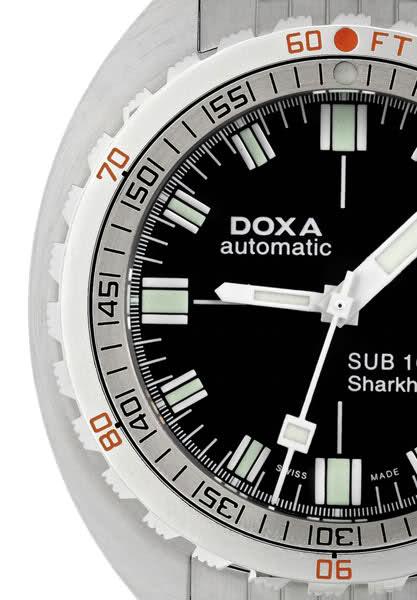
Suche dringend! Spezielle Typo aus den Spätsechzigern
Hallo zusammen, mein erster Beitrag in diesem Forum und gleich eine ganz kniffelige Frage:
Ich suche eine Schrift, die bei Doxa-Taucheruhren aussen auf der Drehlünette graviert ist. Doxa Taucheruhren gibt es seit 1967.
Ich habe schon öfters mal nach dieser Typo gesucht, konnte aber bisher leider überhaupt nichts finden. Sehr einprägsam ist bei dieser Schrift die Ziffer 4, die ich noch nie in der Form gesehen habe als ttf, otf, whatever.
Bei der gesuchten Schrift handelt es sich schoneinmal nicht um die Eurostile, Berthold Gothic oder andere bekanntere Fonts.
Hier ein Bild von der Doxa (ein ganz dolles Teil!) :biglove:
ich würde mal sagen das du diesen font zu 99% nicht finden wirst. das sind ja irgendwelche anfertigungen die direkt für das produkt entwurfen wurden, den ziffern lag sicher kein font zugrunde*. ähnliche sind sicherlich zu finden, wobei man da auch schauen muss ob die diesen abgerundete form besitzen, sowas ist ja eher technisch bedingt.
* kann ja auch nicht, digitale schriften gibt es seit den 80/90ern.
Danke schoneinmal für die erste Einschätzung. Habe diesen Font schon öfters mal bei einer älteren Uhr gesehen, besonders markant und formschön halt die "4". Naja, ich werde noch weitersuchen, ansonsten bleibt mir wohl nur der Weg des Nachbauens in Illustrator...
Ich stimme mit Vorbehalt zu. Allerdings würde ich die Aussage etwas erweitern: Es existieren sicherlich handgemachte Schablonen und/oder Fräsmuster. Das sind dann aber nicht immer Einzelexemplare. Ein Blick zu Werkzeugherstellern sollte vielleicht sogar ähnliche Schriften zum Vorschein bringen. Aber dann hat man immer noch nicht den ,,Font'' in elektronischer Form. Ab den 1970ern gab es diese dann auch auf der Basis von verschiedenen Normschriften (Schablonen). Bei CAD-Weichware werden einige der Schriften aus den 1970ern mitgeliefert (*isocp*.ttf und *isoct*.ttf), aber diese unterscheiden sich stark von der Vorlage. Am Zusammenklicken führt IMHO kein Weg vorbei. Das sollte aber bei diesen geometrischen Schriften einfach sein. Mit Inkscape geht sowas recht gut. Abgrundete Rechtecke, Rand passend definieren, Kontur nach Pfad und dann u.U. Pfad vereinigen ...
Hallo, ich habe eine für mich optimale Lösung gefunden:
Habe die Ziffern in Photoshop nachgebaut inkl. verschiedener Kurvenradien, das schaffe ich da viel schneller als in Illustrator. Habe dann versucht, die Ziffern in Illustrator per Abpausfunktion zu vektorisieren, doch das Ergebnis war sozusagen mangelhaft. Die Rettung kam dann mit dem Programm Vector Magic, alles lief prima, so wie ich es mir vorgestellt hatte!